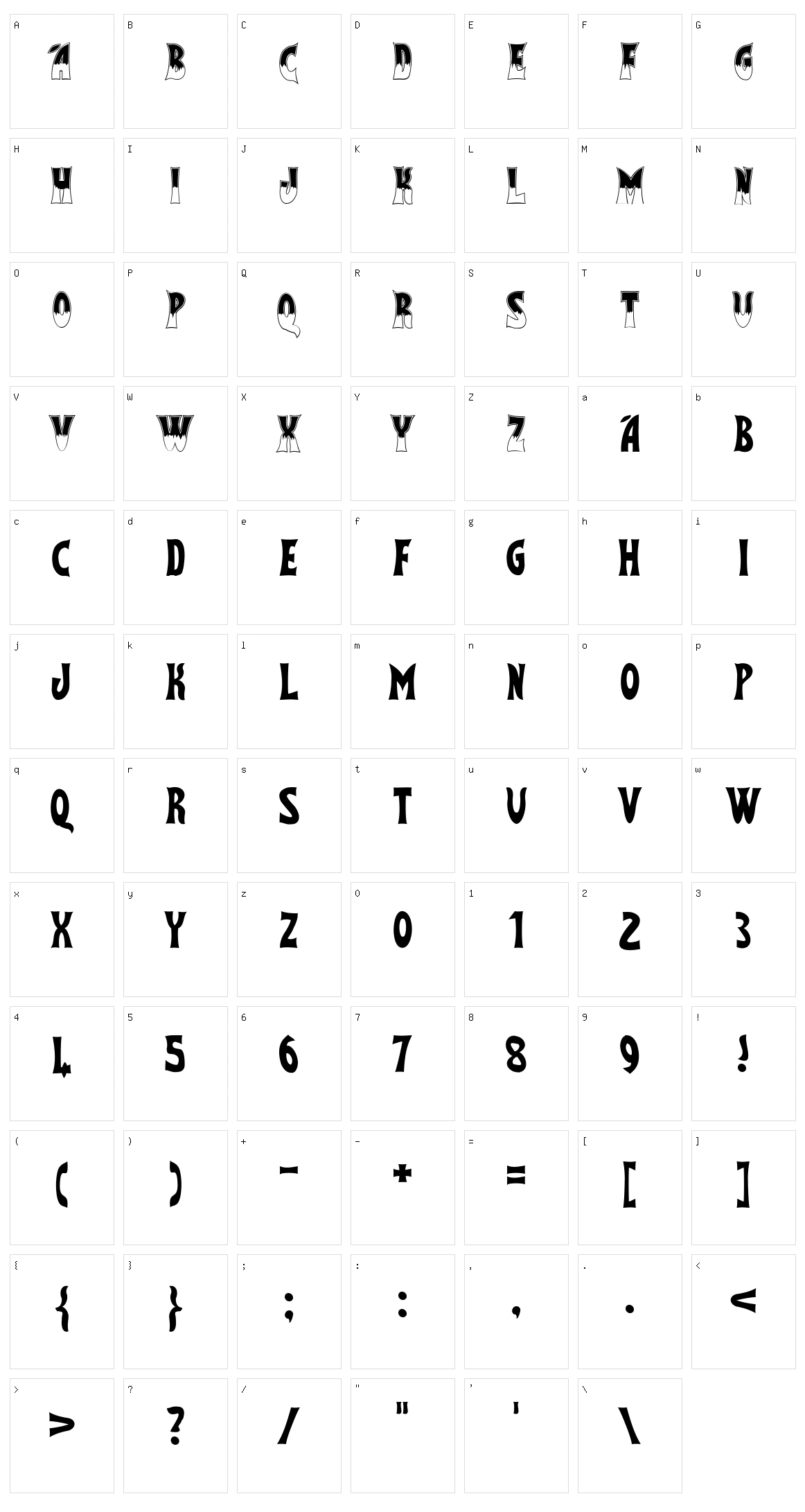
Font name: Flash Gordon FONT (Max Von Sydow Collection) - Latin Decorative font (versione 1.0)
Type designer: P. A. Vannucci
Flash Gordon font: direttamente dal film diretto da Mike Hodges,interpretato
da un ottimo Max Von Sydow, il font inedito per tutti gli estimatori
del film. Da notare il ritocco necessario in Photoshop per conferire, alla titolazione, l'originale bordatura.
Flash Gordon font: directly from the Best movie by Mike hodges, with Max Von Sydow,
the original font for all lovers. Use ADOBE Photoshop for the original border from title.